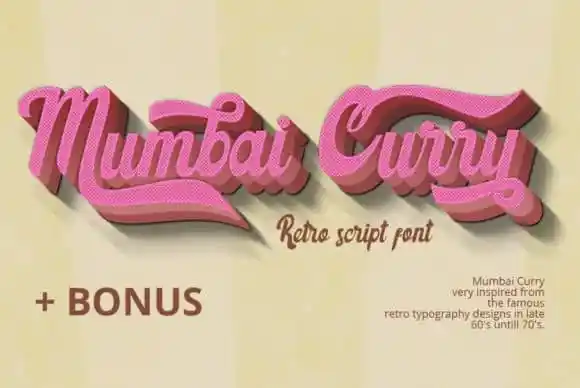
Mumbai Curry Script Font
A fonte ‘Mumbai Curry Script Font’ é uma escolha perfeita para designers que desejam adicionar um toque vintage e nostálgico a seus projetos. Essa fonte de script Mumbai Curry traz consigo uma extra versão Extruded e uma outra chamada Outline, permitindo criar efeitos extrusivos fascinantes. Ela foi criada e compartilhada por anomali.bisu, oferecendo um design leve que envolve o sentimento nostálgico de uma Mumbai mais velha. Esta fonte é perfeitamente adaptável para qualquer projeto em destaque ou visual gráfico que esteja buscando incorporar um ar retro. Perfeita para aqueles desejando dar um toque especial ao seu design, seja para títulos, sublinhados ou até mesmo para adicionar um texto em uma página web, a Mumbai Curry Script Font garante aquela sensação de nostalgia e encanto vintage que faz qualquer projeto brilhar.